사용자를 위한 타이포그래피 체계
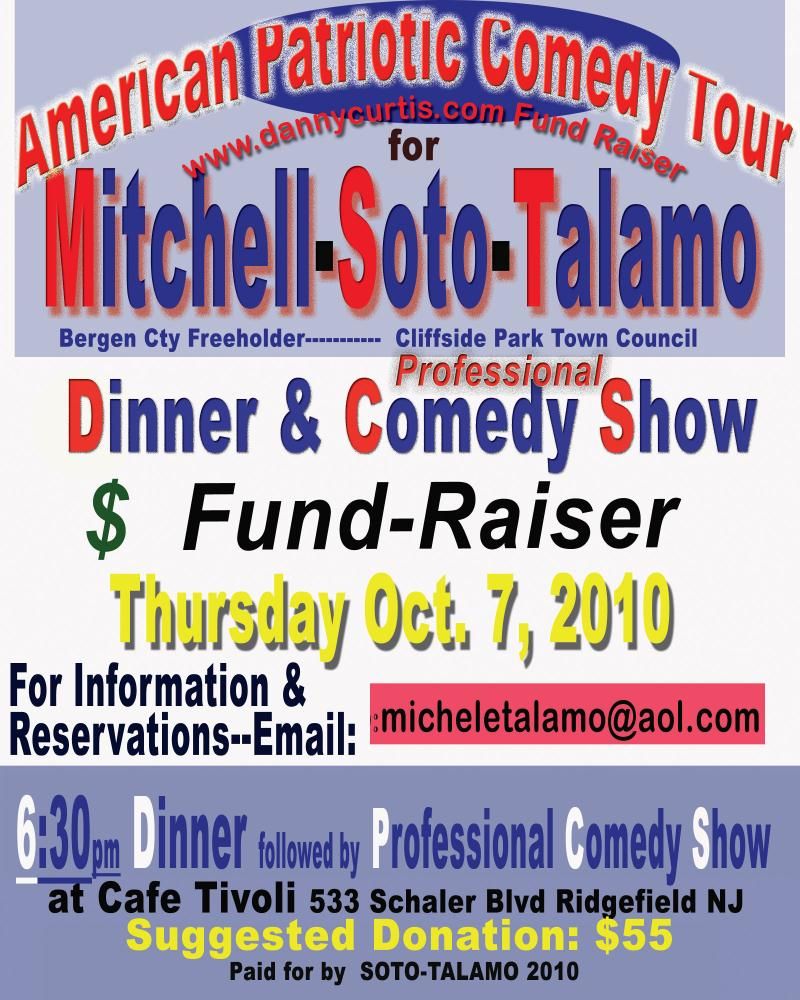
텍스트도 체계가 필요해!
혹시 길을 걷다가 전단지나 포스터를 봤는데 이해가 안 가서 한참 동안 들여다봐야 했던 경험이 있나요? 디자인 비전공자가 흔히 범하는 실수가 본인이 만든 콘텐츠를 강조하고 싶은 나머지 모든 텍스트에 여러 효과를 때려 박는 넣는다는 것입니다. 하지만 이런 난잡한 텍스트 효과는 시각적 잡음만 생성할 뿐 정보전달에 도움이 되지 못합니다.
그럼 어떻게 해야 할까요?
타이포그래피 체계 (Typographic Hierarchy)
텍스트를 중요성의 순서대로 정리하여 사용자들이 원하는 정보를 쉽게 찾고, 빠르게 접근할 수 있게 도와주는 시스템을 타이포그래피 체계라고 합니다. 성공적인 타이포그래피 체계는 아래와 같은 두 가지 장점이 있습니다.
1) 사용자가 원하는 정보를 빠르게 찾고, 콘텐츠를 살펴보기 쉽게 도와줍니다.
2) 콘텐츠의 시작과 끝을 알려주어 사용자의 눈이 특정 정보를 분리하여 확인할 수 있게 도와줍니다.
오늘은 타이포그래피 체계를 구성하는 요소들과 사용법에 대하여 알려드리려고 합니다.
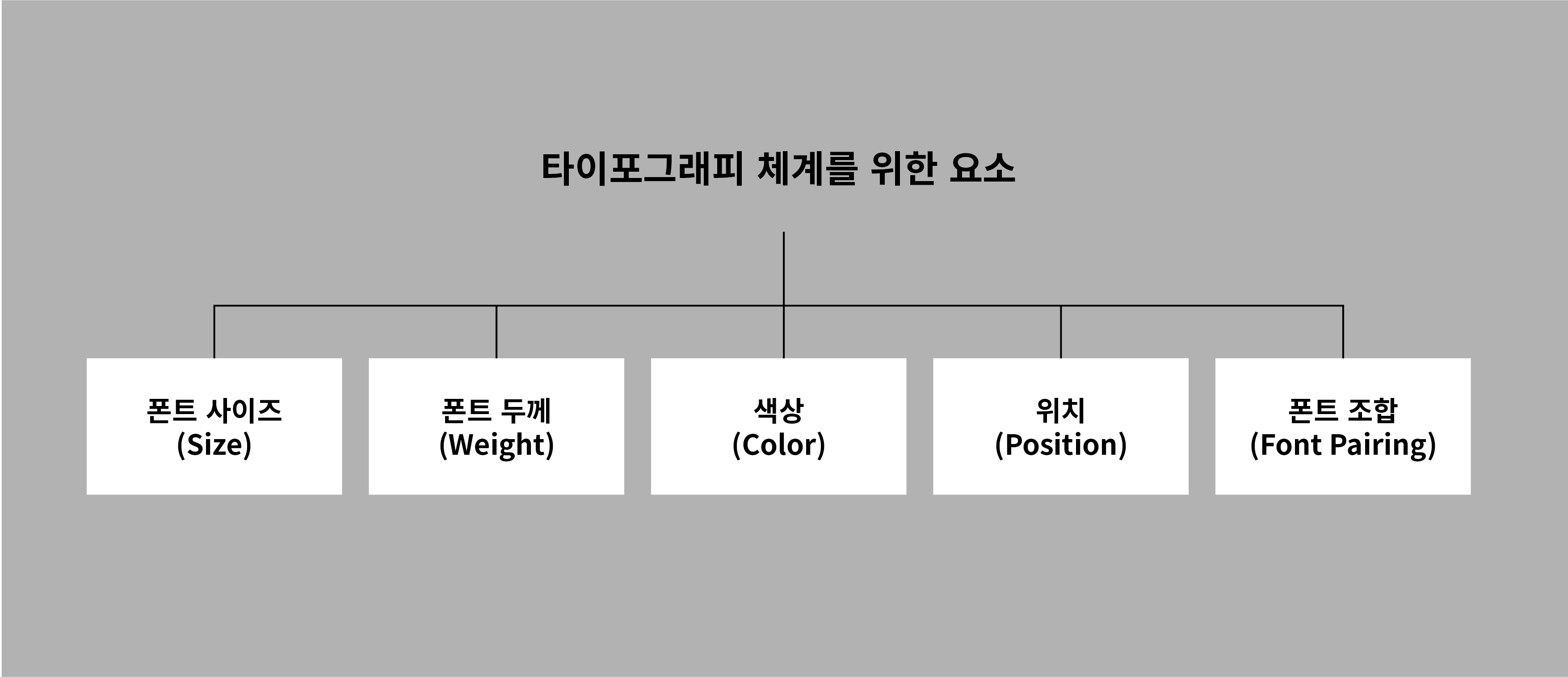
1. 폰트 사이즈 (Size)
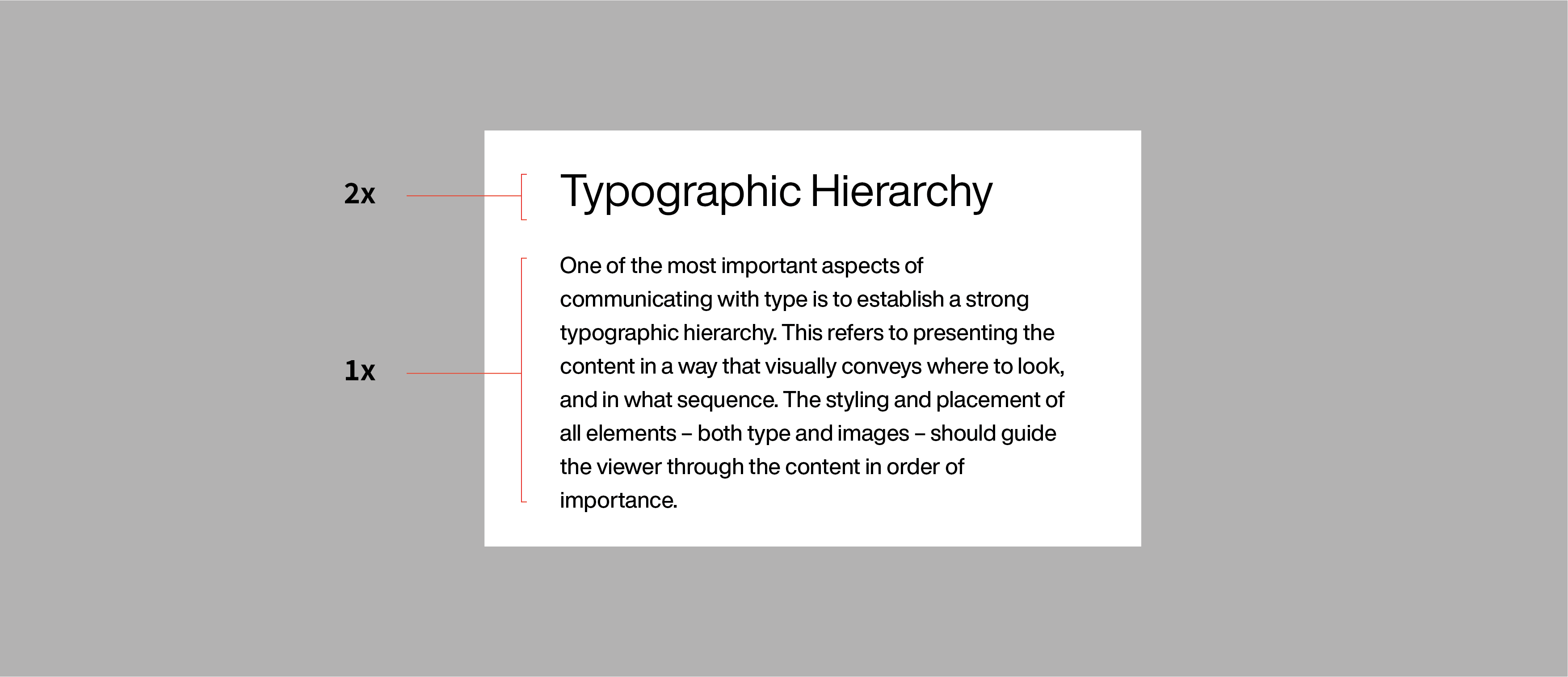
글자의 크기는 위계질서를 세우는 가장 쉽고 흔한 방법입니다. (다만 본문용으로 제작된 폰트일 경우 헤드라인용 폰트보다 자간이 넓게 세팅되어 있기 때문에, 타이틀로 활용 시에는 자간을 살짝 줄이는 것을 추천드립니다.)
헤드라인의 텍스트 크기를 본문용 텍스트의 두배로 설정하면 쉽게 명확한 대비를 줄 수 있습니다. 하지만 전체 면적이 좁은 모바일 UI을 위해 디자인하거나 헤드라인, 본문 텍스트 이외에 부가적 요소들이 추가되면 각 요소들의 크기가 섬세하게 조정돼야 할 필요가 있습니다.
2. 폰트 두께 (Weight)
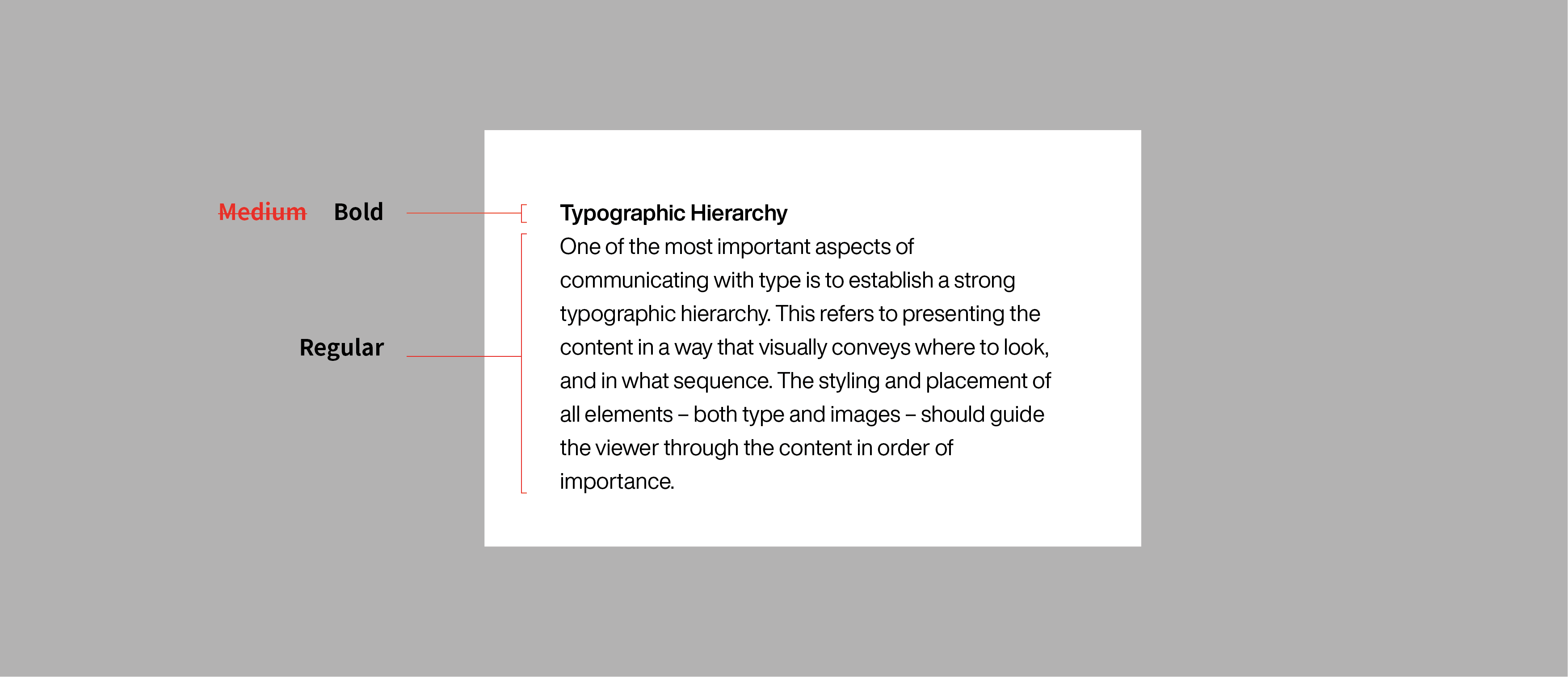
한 서체 내에서 여러 두께의 폰트를 사용하여 위계질서를 세울 수도 있습니다. 하지만 글자의 크기가 같을 경우 명확한 대비를 위해 폰트의 두께 차이가 한 단계 이상 차이 나야 합니다. 예를 들어 본문용으로 Regular를 사용하신다면 타이틀은 다음 두께(Medium)가 아닌 Bold를 사용하셔야 합니다.
예시
본문: Regular -> 헤드라인: Bold 이상 두께
본문: Medium -> 헤드라인: Extra Bold 이상 두께
3. 폰트 색상 (Color)
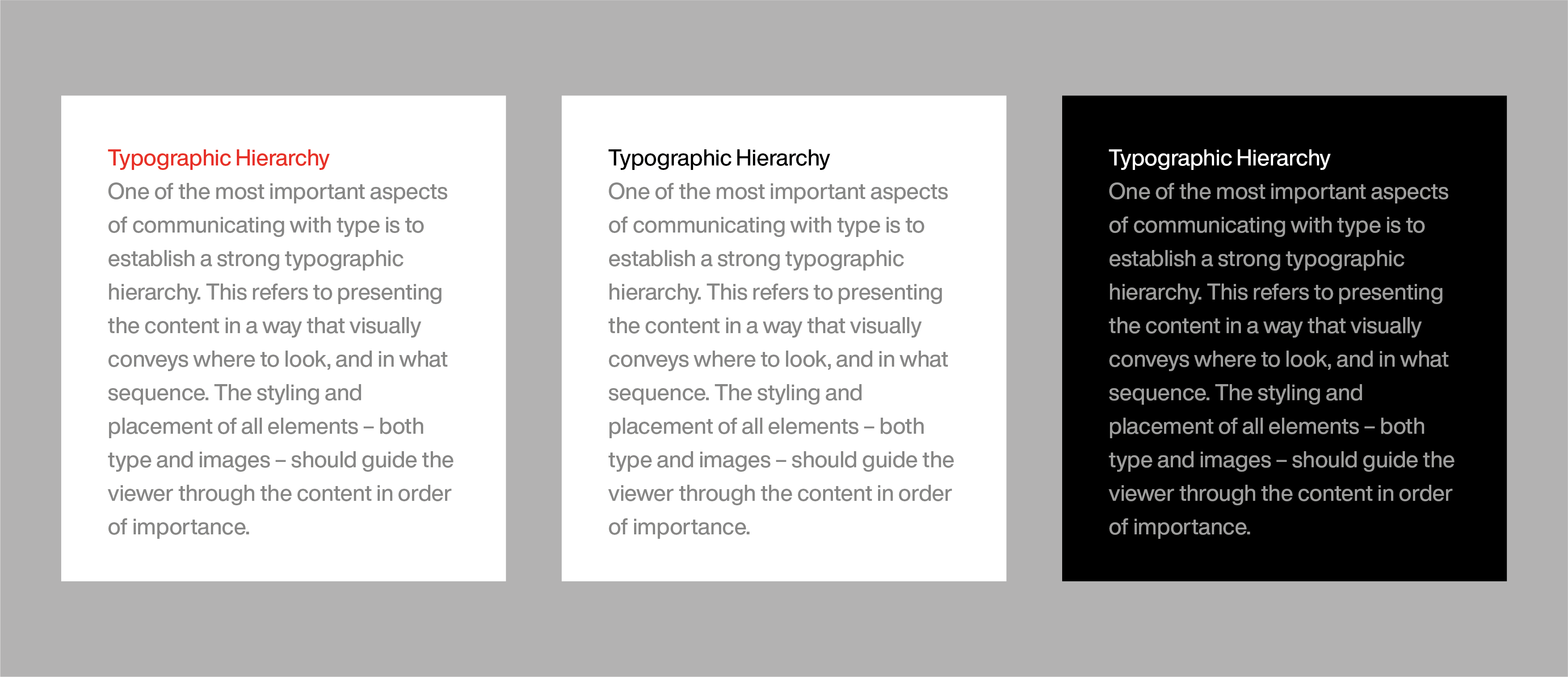
글자의 색상은 눈이 시각적 정보를 받아들이는 순서에 큰 역할을 합니다. 따듯한 계열의 색상은 눈에 띄고, 차가운 색상은 뒤로 물러납니다. 색상뿐만 아니라 텍스트의 명도를 이용함으로써 자연스러운 위계질서를 구성할 수 있습니다.
배경에 색상을 사용할 경우, 텍스트와 배경과의 충분한 대비가 이뤄져야 가독성을 높일 수 있습니다.
4. 위치 (Position)
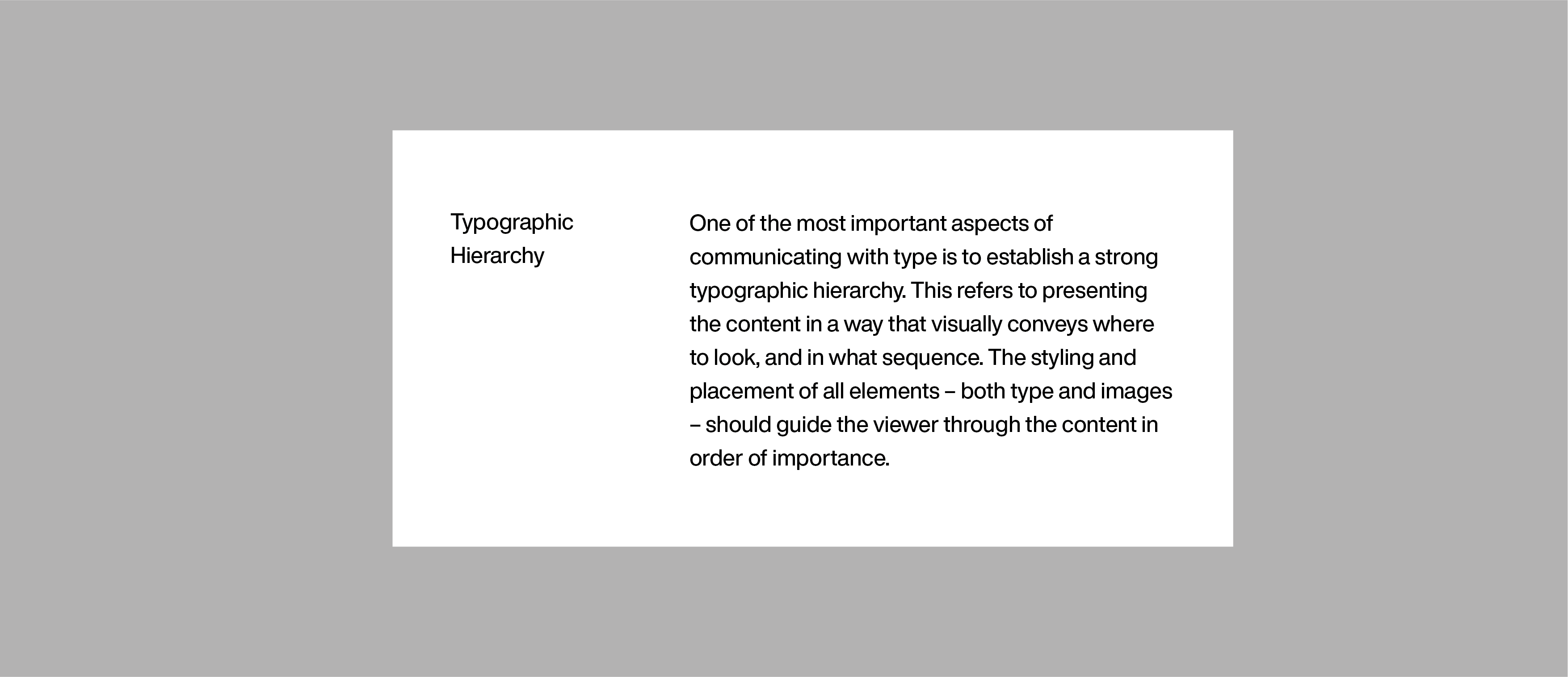
텍스트의 위치는 다른 텍스트들이 어떠한 관계에서 위계질서를 가지고 있는지 알려줍니다. 한 섹션에 포함되는 요소들이 서로 너무 떨어져 있으면 사용자가 독립된 정보로 인지 할 수 있음으로 유의해주세요.
5. 폰트의 조합 (Font Pairing)
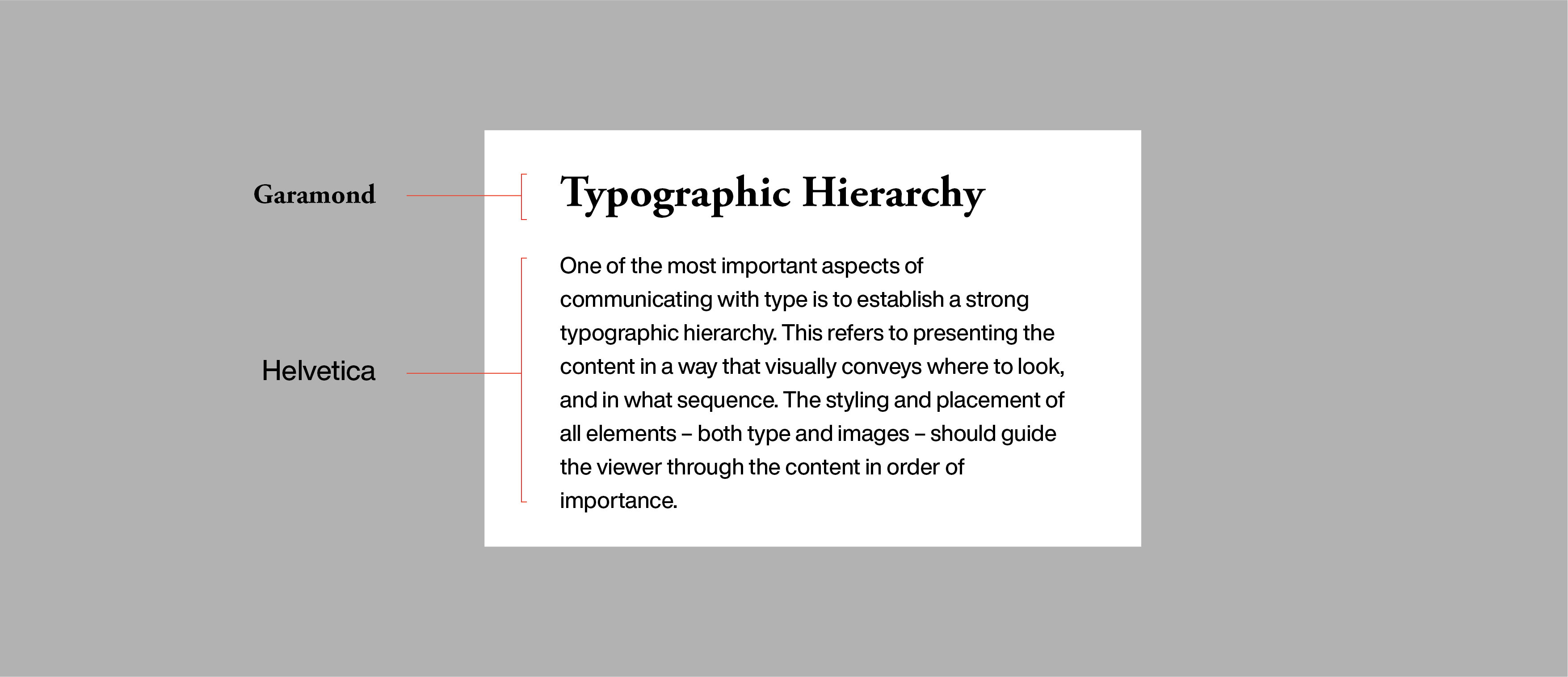
서로 다른 서체의 폰트를 조합하여 대비를 줌으로써 체계를 잡을 수도 있습니다. 폰트 조합 시에 두 폰트 모두 스타일이 너무 강하면 시각적 잡음을 생성할 수 있으므로 피하는 게 좋습니다.
이런 폰트 조합을 활용하는 대표적인 예시로는 글쓰기 플랫폼인 Medium이 있습니다.
6. 혹은 위 요소들의 조합
효과적인 타이포그래피 체계를 위해서는 위의 5가지 요소들을 적절히 조합해야 합니다.
아래 예시를 통해 좀 더 자세히 알아봅시다.
| 예시
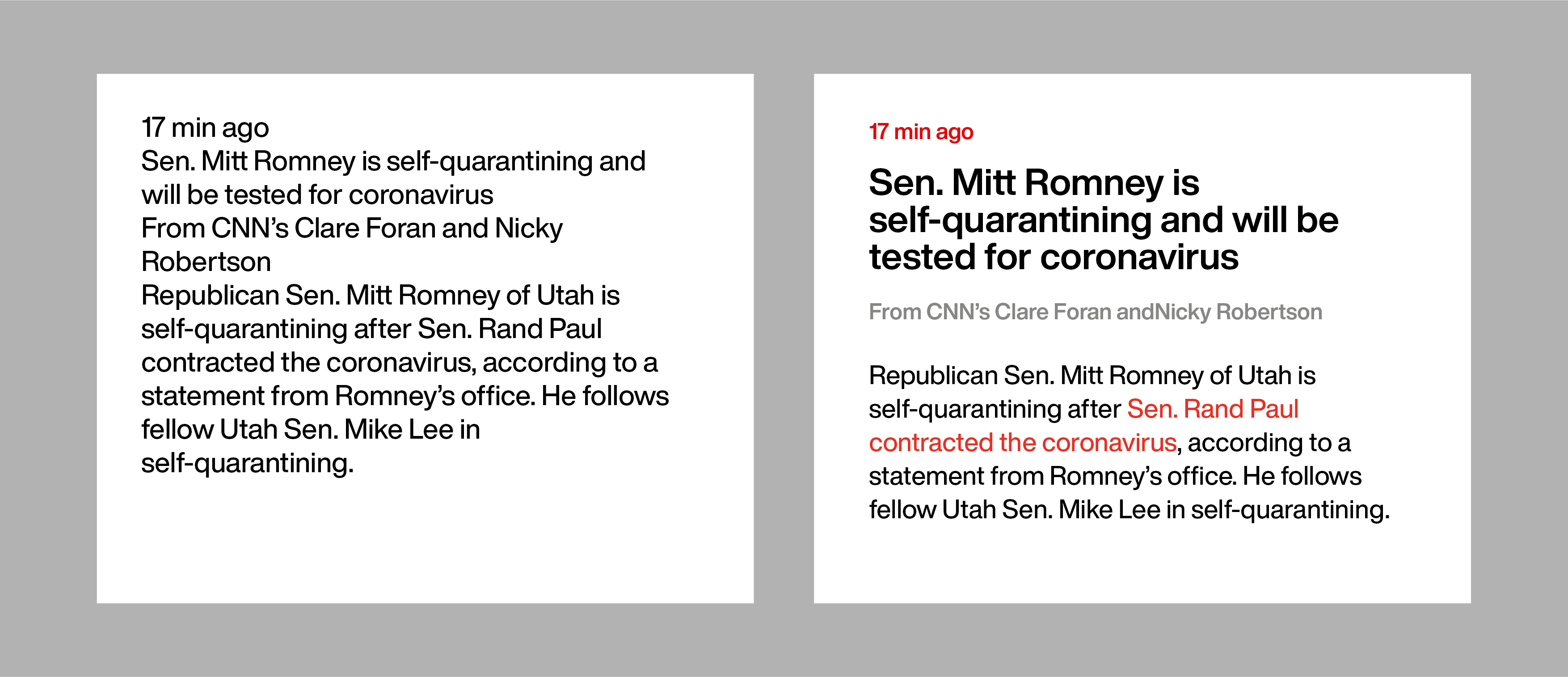
CNN에서 코로나 관련 뉴스 속보를 텍스트로 가져와 가벼운 예시를 만들어보았습니다. 어떤가요?
좌, 우 이미지는 분명 같은 정보를 담고 있지만, 정보 획득의 속도에서 확연한 차이가 납니다. 사용자는 이 뉴스 속보에서 정보들을 분류할 수 있고, 필요한 정보만 뽑아서 읽기 용이합니다.
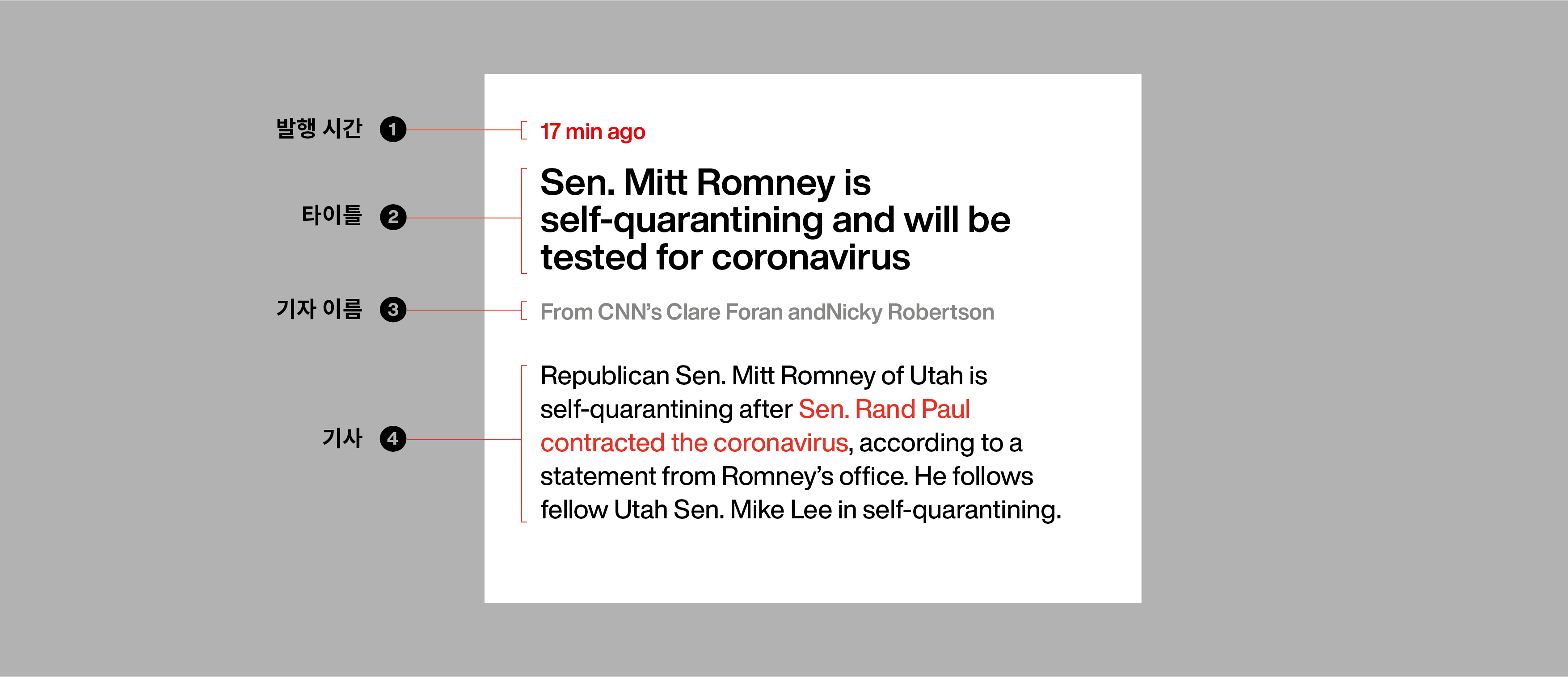
이 짧은 뉴스 속보를 분석하면 크게 네 가지 정보가 있습니다.
#1 발행 시간 (우선순위 3)
발행 시간은 타이틀과 기사보다 우선순위가 낮음으로 다소 작은 사이즈인 12pt이나, 뉴스속보라는 콘텐츠의 특성상 시간은 중요한 요소임으로 밝은 레드 계열을 사용하여 강조했습니다.
사이즈: 12pt / 두께: Bold / 색상: C0 M100 Y100 K0
#2 타이틀 (우선순위 1)
어떤 콘텐츠이든 타이틀은 가장 이목을 끌어야 합니다. 사용자가 다음 정보를 이어나가 볼지 결정하게 만들기 때문입니다. 따라서 모든 요소 중에서 가장 크며, 배경과의 대비가 제일 큽니다.
사이즈: 20pt / 두께: Bold / 행간: 20pt / 색상: C0 M0 Y0 K100
헤드라인의 행간이 너무 넓어질 경우, 느슨해 보여 집중력을 저하시킬 수 있음으로 글자 크기와 행간을 같은 크기로 설정했습니다. 영문 타이포그래피에서는 이를 Set Solid라고 합니다.
#3 기자 이름 (우선순위 4)
이 콘텐츠에서 가장 낮은 우선순위를 가지고 있음으로 본문과의 대비를 위하여 회색을 사용했습니다.
사이즈: 12pt / 두께: Bold / 색상: C0 M0 Y0 K60
시각적 우선순위가 낮음에도 Bold 두께의 폰트를 사용하는 이유는 다른 요소들에 비해 글자 크기가 작아 상대적으로 획이 너무 얇아 보일 수 있기 때문입니다.
#4 기사 (우선순위 2)
이 콘텐츠에서 두 번째 우선순위를 가지고 있습니다. 따라서 타이틀보다는 작지만 다른 요소보다는 다소 큰 14pt이며 텍스트 색은 검은색으로 지정했습니다.
사이즈: 14pt / 두께: Regular / 행간: 18pt / 색상: C0 M0 Y0 K100
행간은 글줄 길이에 따라 적당히 조정돼야 하며 글자크기의 두배(Double spacing)를 넘지 않게 합니다.